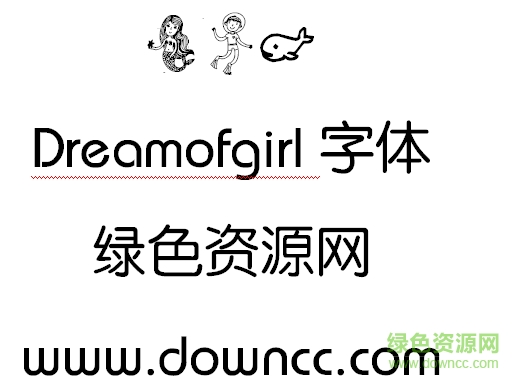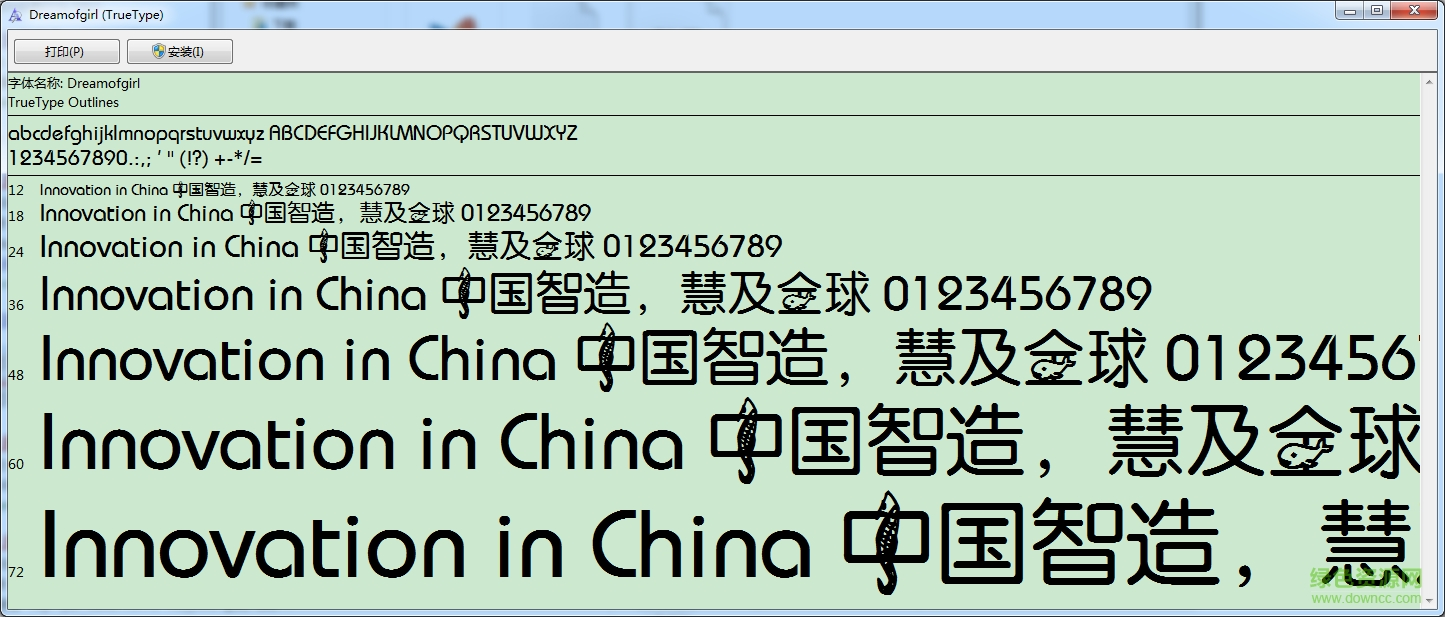
dreamofgirl字體是一款美人魚(yú)字體,一條活潑的人魚(yú)游動(dòng)在你的文字指尖,一會(huì)豎起頭欲躍出水面,一會(huì)在水滴盤(pán)旋,非常生動(dòng),喜歡就快來(lái)綠色資源網(wǎng)下載吧!
dreamofgirl是一款中文簡(jiǎn)體,在碰到特殊漢字時(shí)會(huì)觸發(fā)美人魚(yú)特效哦,如圖中的“美人魚(yú)”三個(gè)字就是三個(gè)符號(hào),其他的字體也端莊簡(jiǎn)潔,快來(lái)綠色資源網(wǎng)試試吧!
dreamofgirl字體是一款有著好看美人魚(yú)的藝術(shù)字體,藝術(shù)范十足,該字體字庫(kù)完整,海報(bào)、ppt、廣告設(shè)計(jì)等方面都可以使用該款字體。